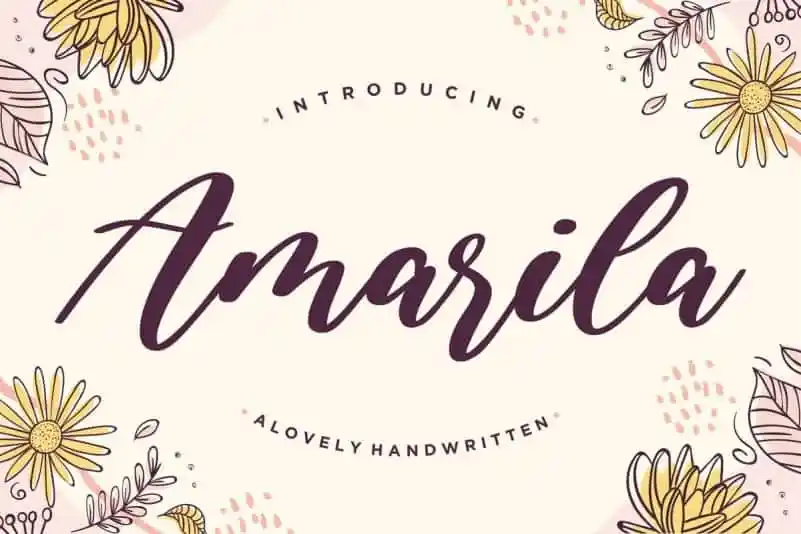
Amarila Lovely Handwritten Font – Download Grátis
Amarila é uma fofa fonte escrita à mão. Essa elegante fonte tem linhas suaves e finas que se assemelham a um lindo traçado de lápis, perfeita para qualquer aplicação visual. Seja para embalagens de produtos, projetos de marca, revistas, mídia social, casamentos ou simplesmente usada como um toque de texto acima do fundo – Amarila atende a todos esses requisitos. A fonte é ideal tanto para usar em texturas mais elaboradas quanto para gráficos mais simples e elegantes. Ideal para quem busca uma fofura única que enriqueça qualquer design visual, não hesite em experimentar o charme deste belo traçado à mão.